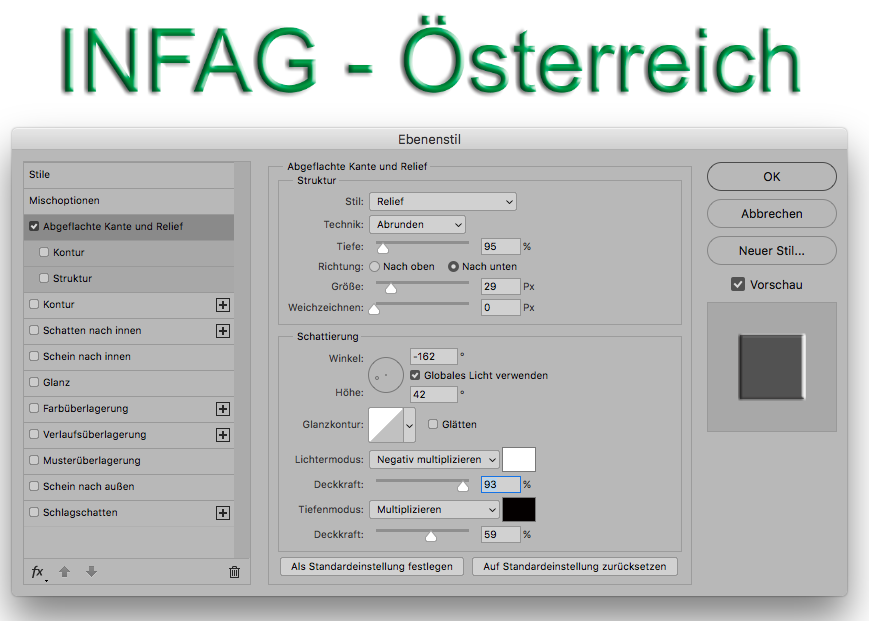
Ich muss für eine Homepage den Schriftzug im Logo erweitern.
Leider hab ich keine Information darüber, wer das Logo erstellt hat und mit welcher App.
Könnt ihr mir helfen:
1. die Schrift zu erkennen
2. mir tipps sagen, mit welchem Programm ich den Text passend ergänzen/erweitern kann.
Das ist die Arial, die 3D-Anmutung kann in Photoshop erstellt werden.
Mit "Abgeflachte Kante / Relief" kommt man ganz gut hin, schnell hingeschubst:
Ich hab zwar Photoshop auf dem PC installiert, kann damit aber leider gar nicht umgehen.
Wäre es möglich mir dein Ergebnis zuzuschicken. Ich wäre dir echt dankbar darüber.
alle Informationen zu dem Effekt sind in dem Screenshot von bertel enthalten.
Photoshop starten, mit dem Textwerkzeug den Text schreiben, einen Ebenenstil hinzufügen, Abgeflachte Kante und Relief, die Einstellungen aus dem Screenshot einstellen oder selbst mit den Werten spielen.
Ich möchte nicht fies klingen, aber warum musst du den Schriftzug erweitern, wenn du mit dem Grafikprogramm nicht umgehen kannst?
Bei der INFAG (Interfranziskanische Arbeitsgemeinschaft) wird sich halt unter den Brüdern und Schwestern niemand gefunden haben, der neben seiner Kirchentätigkeit auch noch als Designer arbeitet … ;-)